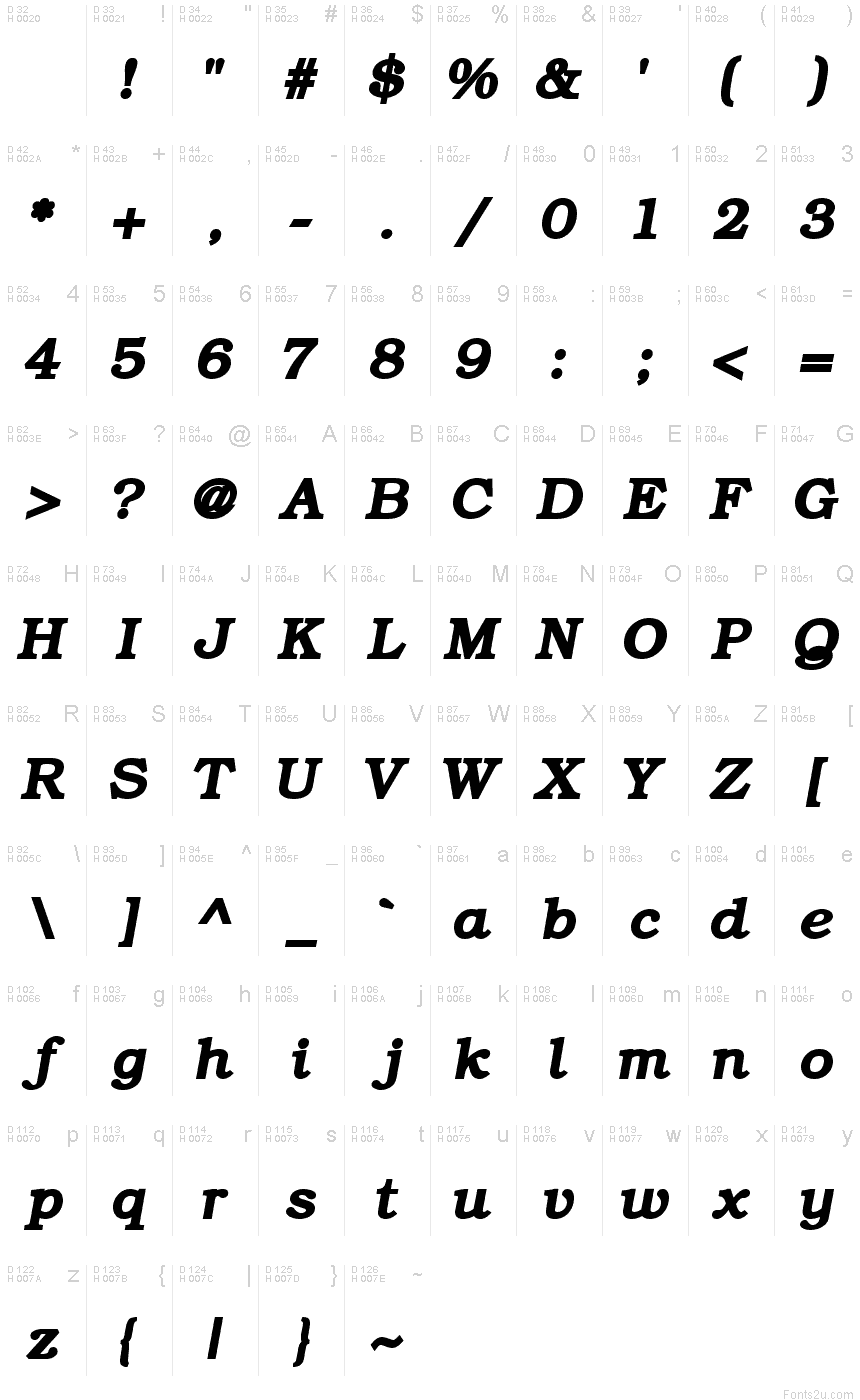
ER Bukinist 1251 Bold Italic
ER Bukinist 1251 Bold Italic autorstwa Gavina Helfa to darmowy, pochyły krój szeryfowy, który przywodzi na myśl klasykę z księgarni, ale w bardziej wyrazistym wydaniu. Jej solidne kreski, ciasny rytm i zdecydowane pochylenie nadają każdemu słowu poczucie pilności, jakby było częścią wciągającej opowieści. Litery sprawiają wrażenie lekko „atramentowych” i skondensowanych, tworząc gęstą, literacką teksturę, która przyciąga wzrok, nie tracąc przy tym na wyrafinowaniu.
Dzięki ER Bukinist 1251 Bold Italic tytuły i nazwy od razu zyskują profesjonalny, wydawniczy charakter, dlatego świetnie sprawdza się na okładkach książek, nagłówkach rozdziałów, w magazynach literackich, przy identyfikacji wizualnej autorów, na plakatach vintage, opakowaniach czy w menu kawiarni. Ten darmowy font najlepiej prezentuje się w dużym rozmiarze, z nieco zwiększonym światłem między literami, co pozwala formom wybrzmieć. W przypadku tekstu głównego warto połączyć go z prostym bezszeryfowym krojem humanistycznym, aby zachować czytelność stron, podczas gdy ER Bukinist 1251 Bold Italic zajmie się narracją w nagłówkach.